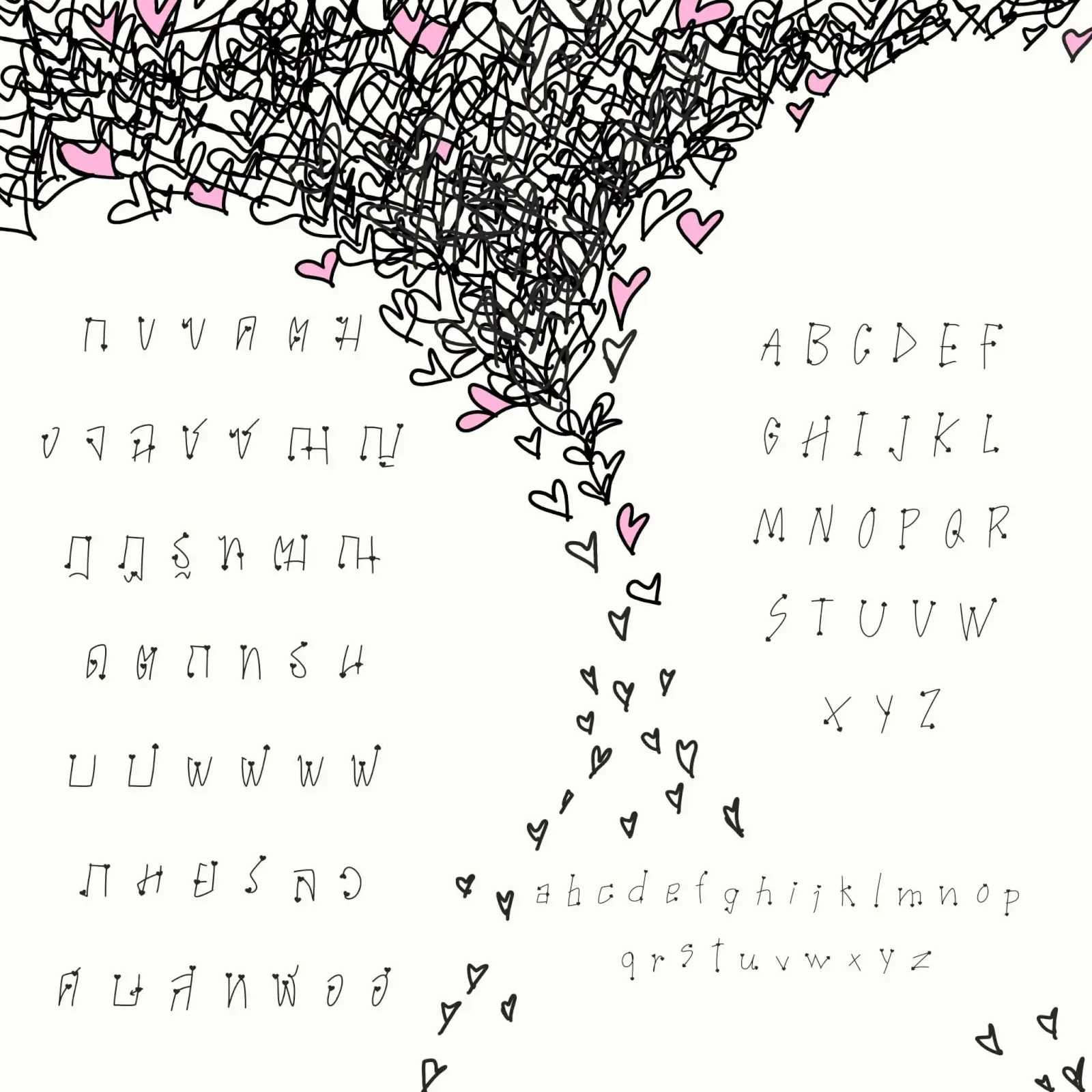
อยากได้ฟอนต์ที่เป็นสัญลักษณ์ของความรัก แบบความรักตรงๆ เลย ไม่ต้องอ้อมค้อม ไว้เป็นของตัวเองสักตัว เลยทำ “ทอศิลป์ รักนะจ๊ะ” ออกมา ออกมาแล้วก็สวยเลยครับ
ฟอนต์ “ทอศิลป์ รักนะจ๊ะ” เป็นฟอนต์ตระกูลเดียวกับ “ทอศิลป์ คิดถึงเธอ” เป็นฟอนต์ลายมือแบบที่ใช้เป็นตัวดิสเพลย์ได้ด้วย
ฟอนต์โดย : ระจัน โรงเรียนสอนศิลปะทอศิลป์
ทอศิลป์ รักนะจ๊ะ (Torsilp RakNaCha)